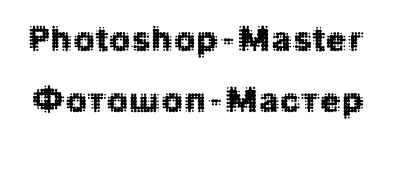
красивый шрифт))
очень интересный шрифт)))спасибо
Ога, крутой)
Кажется что он вот-вот рассыпется х3
Very Cool!супер!
афигенно...респект афтору)))
Аж запестрило в глазах!